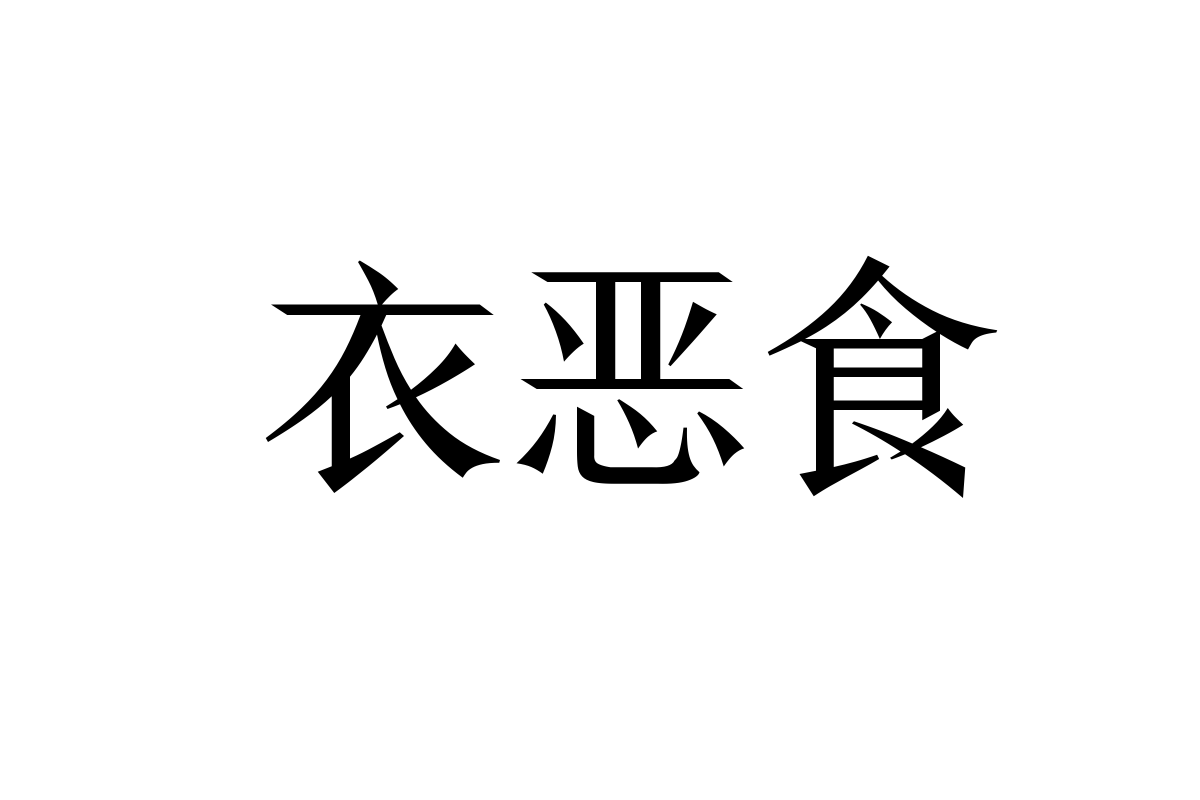
字体管家鬼泣是一款专为游戏《鬼泣》系列设计的字体。这款字体具有独特的风格和视觉效果,能够为游戏场景增添一种神秘而紧张的氛围。它采用了一些特殊的字符和符号,如闪电、火焰、剑等,使得整个字体看起来更加生动和动感。此外,字体管家鬼泣还提供了多种颜色和样式选择,玩家可以根据自己的喜好进行自定义设置。总的来说,这款字体不仅适合游戏使用,也是一款非常实用的字体资源。